ではそんなパワポを作る時に皆さんはどんなことに注意していますか?
このブログでは漢字の画数が多い繁体字で作るパワポはどのように気をつけるべきか、どんなフォントを使えば見違えるようなルックになるかお話をしたいと思います。
フォントの基本
PPT は不親切なことに何十個もフォントがあるため、何を選んでいいかわからないと思いす。その中でもサラリーマンに一番人気なのは「メイリオ」や「游ゴシック体」かと思います。どちらもゴシック体です。そしてとりあえず失敗しないのはゴシック体です。
ゴシック体とはどんなフォントかわからない方のためにまずはゴシック体と明朝体という2種類のフォントについてお話したいと思います。
下にゴシック体及び明朝体を貼り付けました。
(ゴシック体)
(明朝体)
違いがわかりますか?ゴシック体は全ての辺が均一の太さです。
それに対して明朝体は場所によって細い線と太い線があります。(下記参照)
ではなぜゴシック体を選ぶべきなのか?
それは文字の線の太さが均一だと視認性と判読性が優れているためです。視認性とは文字を認識できるかどうかです。判読性とは文字を判別し易いかどうです。
例えば英語のO と 0 (zero) は非常に似通っており、明朝体だとこの判別が難しくなり易いと言われています。実際に明朝体とゴシック体を大小で比較するとどのような違いがあるでしょうか?
下をご覧ください。
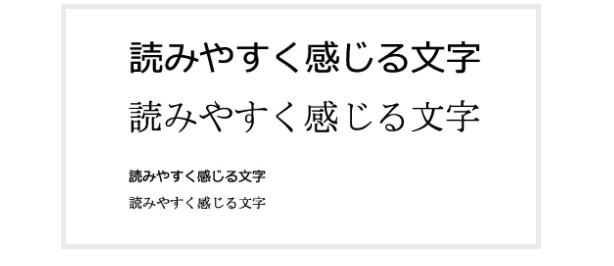
大きいテキストと小さいテキストはそれぞれ上がゴシック体で、その下が明朝体です。
文字が小さくなった途端、明朝体が見にくいと思いませんか?明朝体は文字を小さくすると細い線の部分が見にくくなるのです。これがゴシック体をおすすめする理由です。
ではどんなゴシック体がいいのか?中国語フォントの場合
台湾にいるとどうしても繁体字で資料を使う機会が増えます。ではオススメの中国語のフォントはどれでしょうか?私は中国語で ppt を作る場合は Noto sans CJK TC を使うといいと思っています。
別に私は中国語のフォントにものすごく詳しいわけではありませんが Noto sans CJK TC はフォントのウェイト (太さ) が 豊富に種類があるため使い勝手がいいのです。中国語フォントは最近ライセンス費用の取り締まりも強化されているので Noto sans のようなフリーフォントは嬉しいですよね!
それでは Noto Sans CJK TC を詳細にみていきましょう。
一番左から細い→太い順に並んでいます。こんなに種類が必要か?と思ってしまうかもしれませんが種類が多いと便利なのです。
例えば太さの種類が一種類しかないようなフォントを使用したとします。以下のようにタイトルと文中のテキストの太さが同じぐらいで文字の大きさを変えた場合どう思いますか?
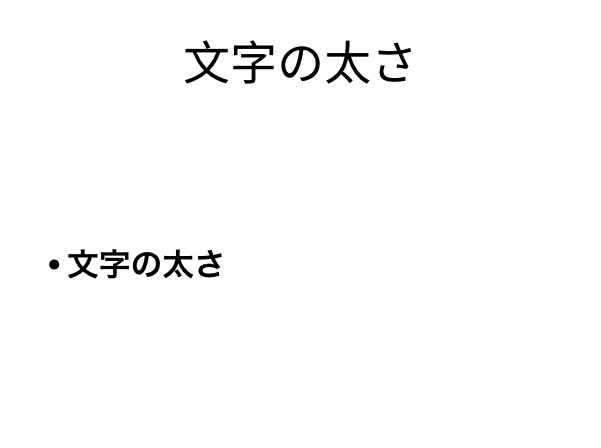
ぱっと見、両方とも同じような大きさに見えませんか?文字の太さが同じだと一方が目立ちにくいため、強調が難しく、焦点が定まりにくいのです。
では上のものとは逆に下をご覧ください。タイトルの文字のフォントの太さを一番太くし、文中の太さを少し落としました。これだけで視線がタイトル→文中という順にスムーズに行きます。
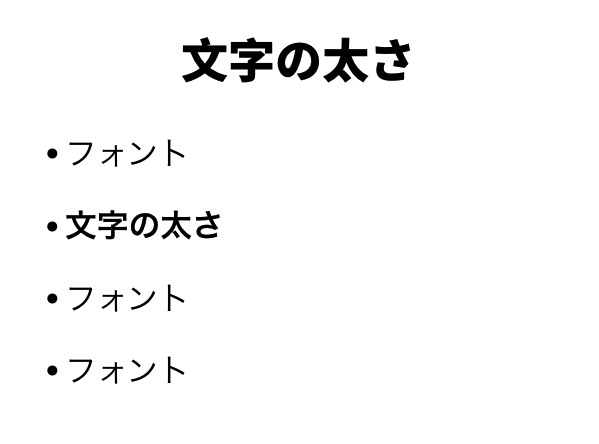
ひとまずここではフォントのウェイト(太さ)の種類が多いと便利ということを覚えておいてください。そして中国語のフォントで太さの種類が豊富にあるのが noto sans CJK TC です。(その他もあるため、これが絶対ではありません)
これだけは避けてほしいフォント
最後に、これだけは避けたほうがいいというフォントをご紹介します。
MSP ゴシックだけは使わないでください。古い windows のデフォルトフォントなので未だによく見ます。悲しくなります。MSP ゴシックのひらがなはサイズの統一性がなく、本当に見にくいです。台湾にいる駐在員さんの資料や台湾の会社員さんの資料で見たときはため息が出ます。